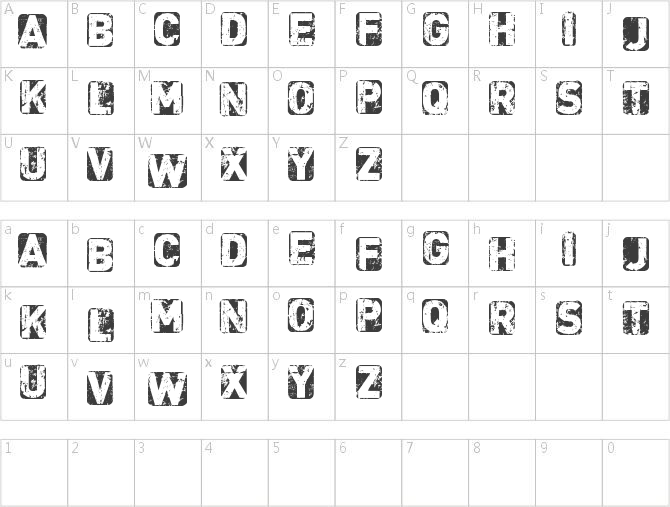
CFPunkisnotDead-Regular 詳情頁
CFPunkisnotDead-Regular字體字庫是一款讓人賞心悅目、百看不厭的英文字體,適合各類廣告和產(chǎn)品包裝設(shè)計(jì)應(yīng)用,字體大小0.23MB,格式為ttf字體,上傳用戶是lvpyt,作者/版權(quán)方為未知